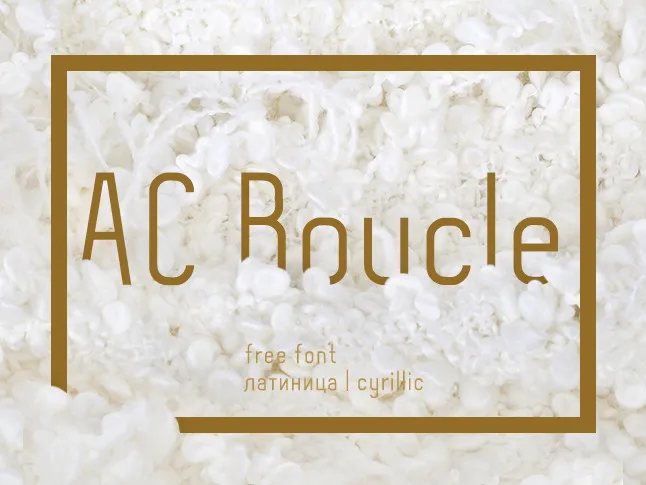
AC Boucle Font foi criado para headlines e tiposetting de texto, adaptado especialmente para designers que buscam uma alternativa ao costumeiro “fence” tipo letra em caixas quadradas. Esta fonte Cyrilica não apresenta a aparência daquela famosa estrutura retangular, mas sim os desenhos arredondados e ondulantes associados à lã de bouclé, dando um toque acolhedor às letras. Este é um excelente recurso para quem procura uma fonte sem serif que ofereça um look sofisticado e atemporal, combinando praticidade com estilo. Hamilton, o designer desta criação, certamente soube explorar as nuances da fonte de forma inspiradora, resultando em uma opção perfeita para gráficos, designers digitais ou quem busca personalização em seu trabalho visual.